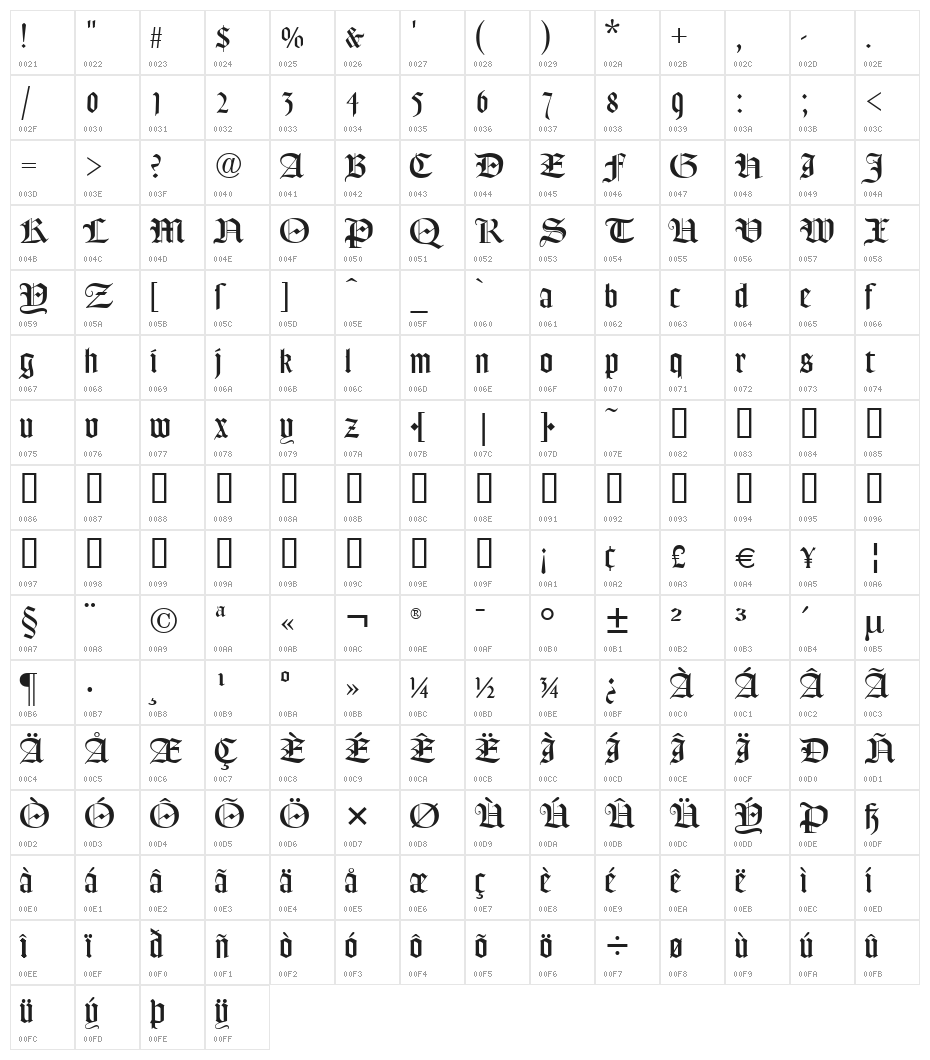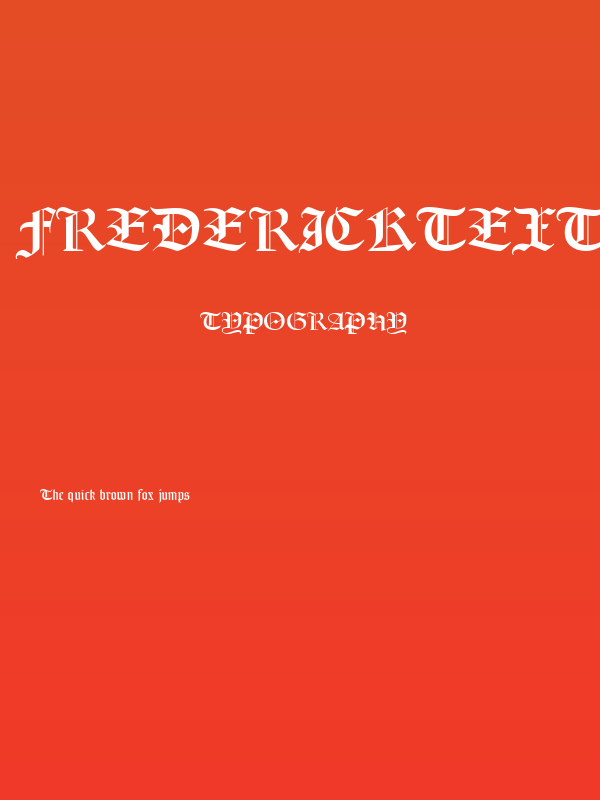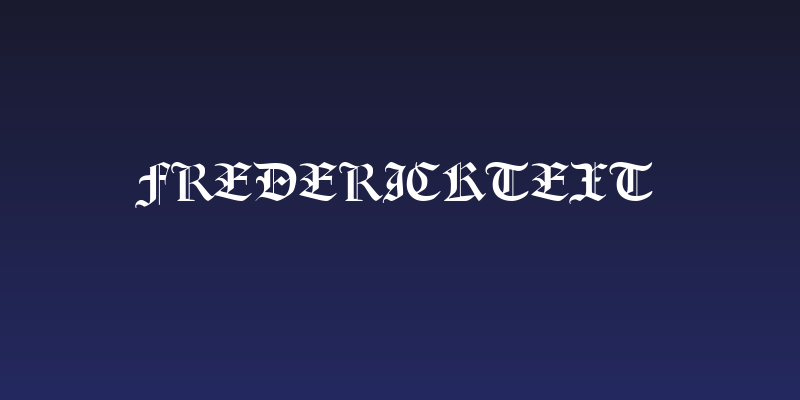
FrederickText Font
Fonts by Dieter Steffmann
| Caso d'uso | Logos, Headlines, Decorative purposes |
| Progetti proposti | Ideal for projects that require a historical or traditional touch, such as invitations, certificates, book covers, or branding for vintage-themed products. |